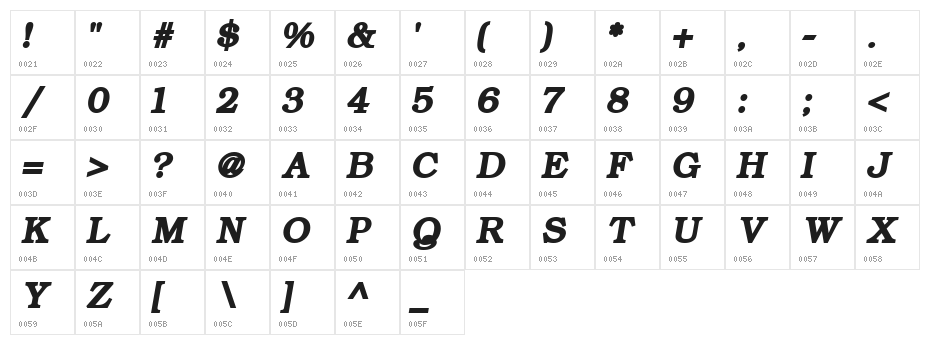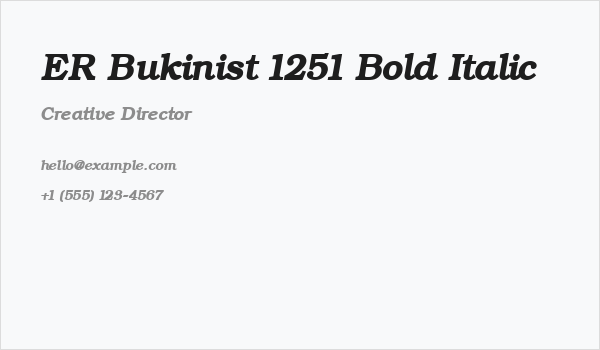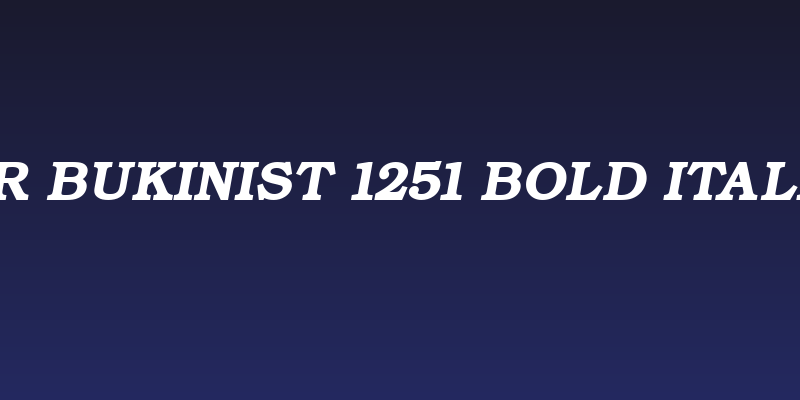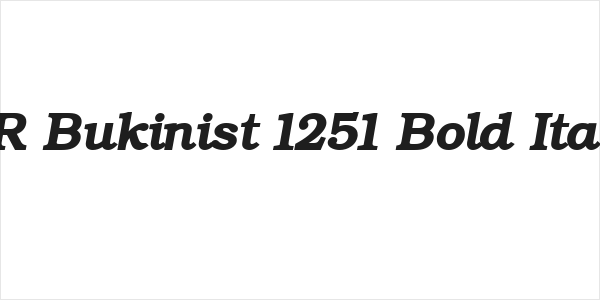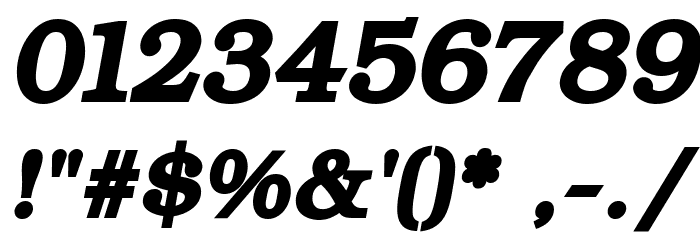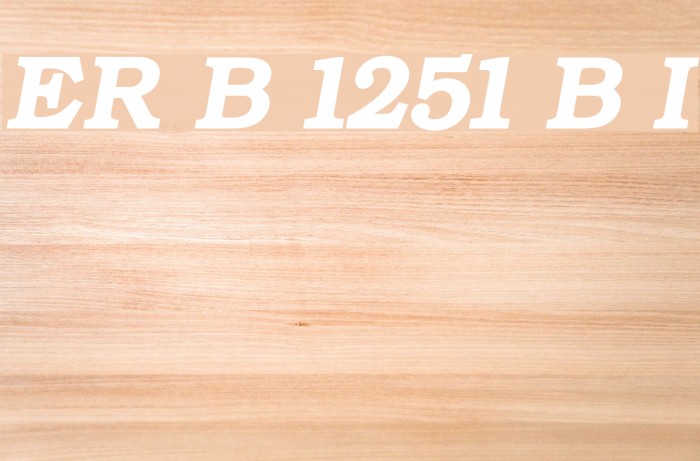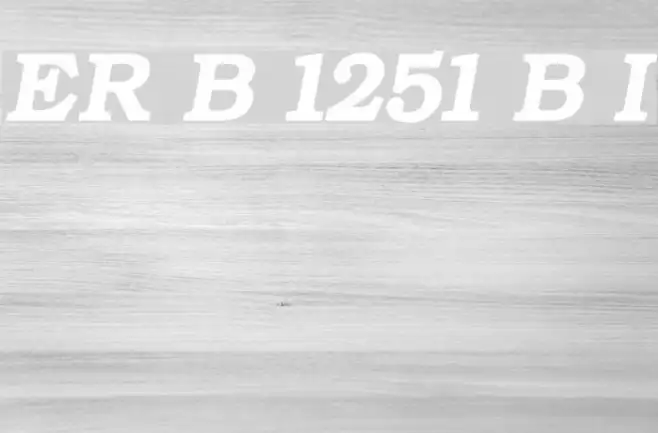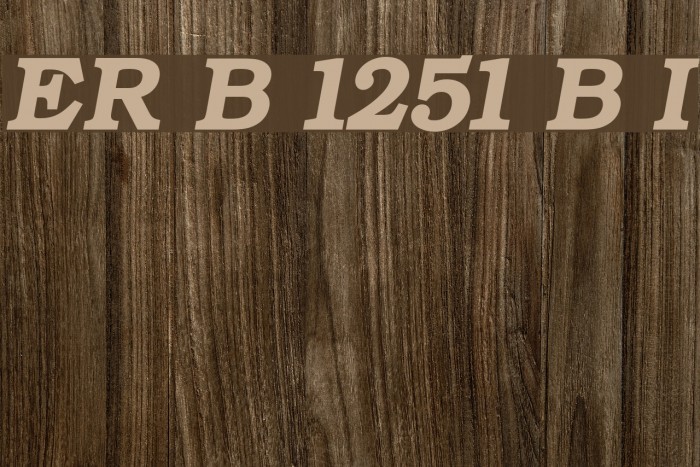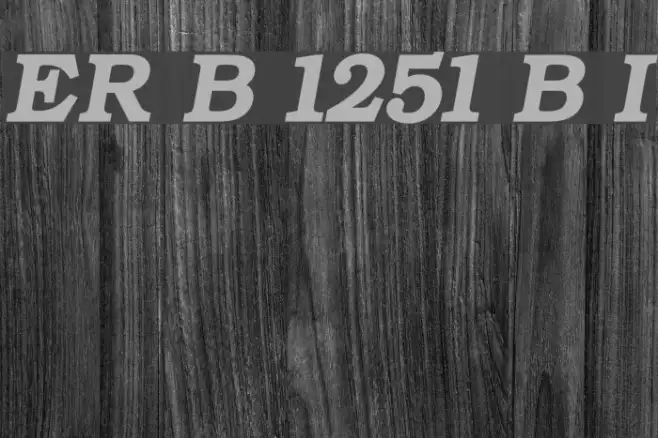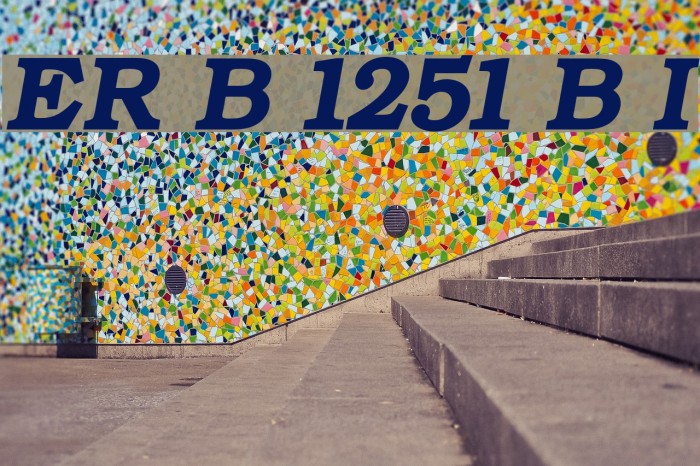
ER Bukinist 1251 Bold Italic Font
| Style général | Classic |
| Projets proposés | Ideal for headlines, posters, branding materials, and any project requiring a bold statement. |